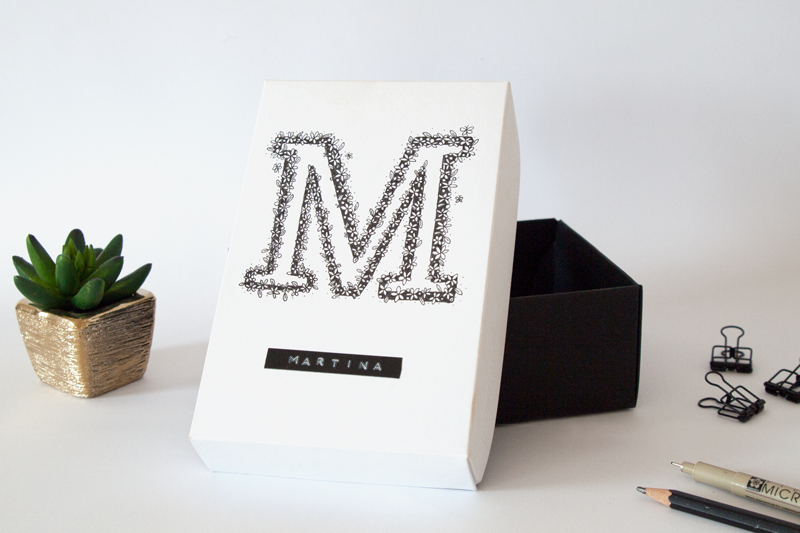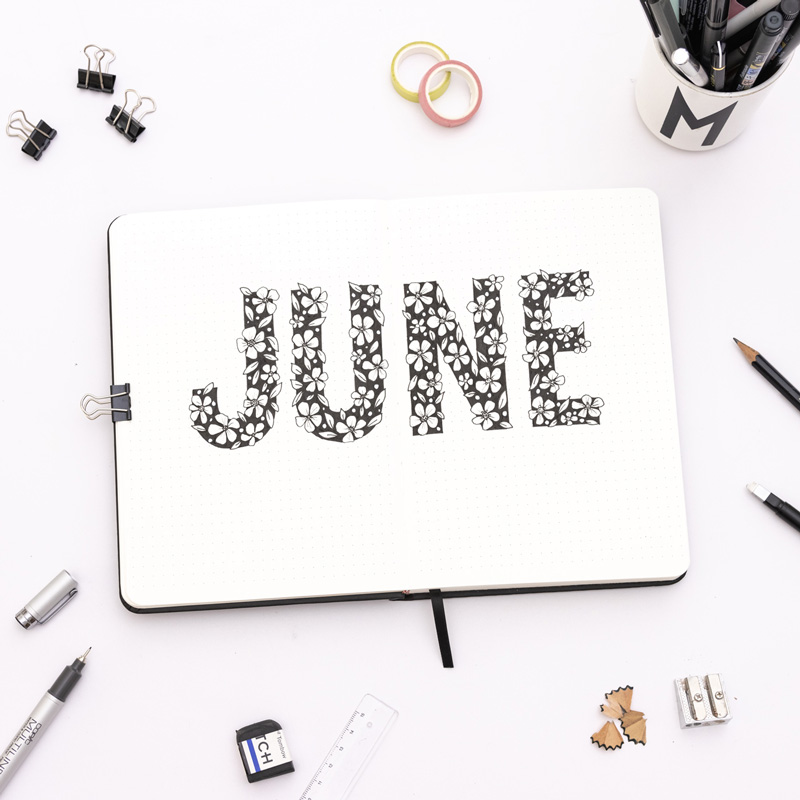
Lettering by Martina Johanna
Hello – nice to meet you!
ich bin Martina Johanna Janssen aus Bremen. Schon als Teenager waren meine Schulhefte voll mit Schriftzügen im Comic, Graffiti oder Kalligrafie Stil. 2014 entdeckte ich dann das Handlettering in den Straßen von Amsterdam, dort findet man an jeder Ecke schöne, handschriftlich gestaltete Tafeln und Schaufenster. Diese haben mich so fasziniert, dass ich am eigenen Schreibtisch direkt meine ersten Handlettering-Versuche mit Bleistift und Fineliner machte. Nach den ersten Versuchen und viel Übung hat mich das Lettering immer mehr begeistert und mittlerweile hat es sich zu meiner großen Liebe und Leidenschaft entwickelt.
Mein Debüt als Hand Lettering Dozentin habe ich im April 2016 auf dem Designmarkt „besonders schön“ in Hamburg gegeben. Seit April 2017 biete ich regelmäßig Handlettering Workshops (mittlerweile in ganz Deutschland) an. Es macht mir super viel Spaß mein selbst erlerntes Wissen weiterzugeben und Menschen mit dem Lettering Fieber anzustecken.
In den Workshops möchte ich euch inspirieren & motivieren und vielleicht auch ein kleinwenig verzaubern!